车载字体
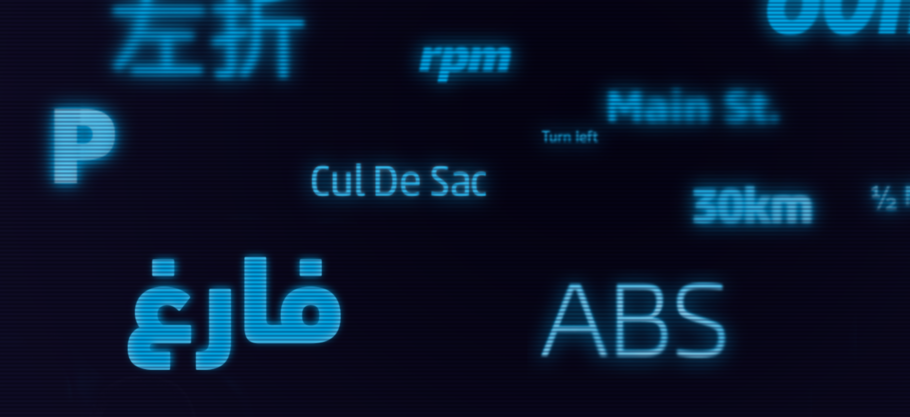
快速获取信息比时速 60 英里重要得多!车用字体必须具有视觉吸引力和品牌一致性,同时还要一目了然,清晰易读。本文展示了一系列可以轻松阅读的字体,这些字体还能够帮助驾驶员在行驶过程中保持注意力。
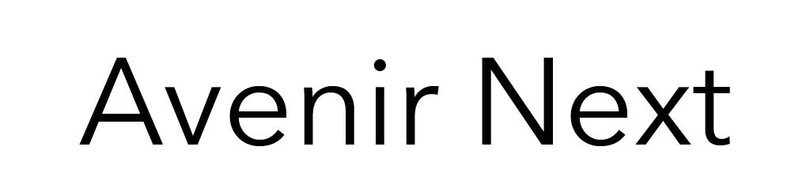
在设计 Avenir® 时,Adrian Frutiger 从过去和未来同时汲取了灵感。Frutiger 在设计中加入了一点有机的人文主义元素,将 Avenir 从早期字体僵硬的几何风格中解放出来。
2004 年,Frutiger 与 Linotype 公司字体设计师小林章一同复刻了 Avenir 字体家族,解决了其屏幕显示的问题。这就是 Avenir Next 字体。几何元素与人文元素的结合造就了 Avenir 字体的高易读性,使其成为汽车人机界面仪表盘和显示器等快速扫视环境下最理想的选择。
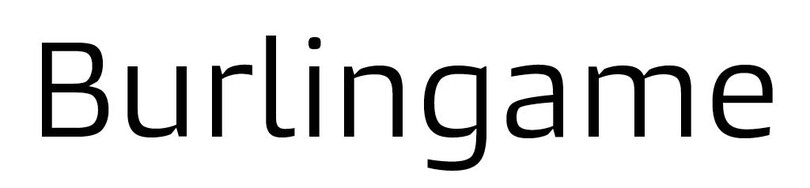
Burlingame® 字体是一款相对较新的字体,它的设计坚实,外形开放、清晰,易读性非常高,尤其对于受限较多的数字化环境。这款字体体现了人文主义及手工质感,根据 Monotype 委托开展的汽车用户界面易读性研究所得到的结果进行了修改,使 Burlingame 成为任何车辆电子仪表盘的不二选择。
Burlingame 字体为了满足汽车显示器的需求融合了多种特性:平整的笔画端头、锐利的转角、“超椭圆” 造型的字碗以及宽松的字间距。其简单的形状和深凹的三角形切口还有助于确保小字号下字体的清晰度和易读性,特别是在低分辨率的屏幕上。
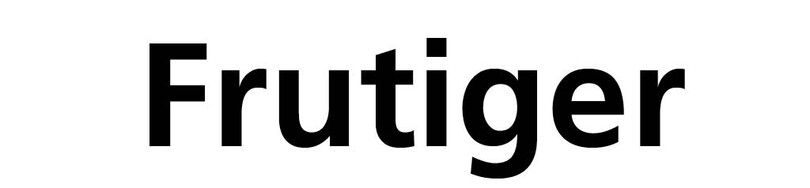
Adrian Frutiger 是世界知名的字体设计师。他的同名字体的设计独具特色,而且用途广泛。Frutiger® 字体最初用于机场导视牌,在远距离及多种角度下阅读都非常清晰。作为一款经典字体,Frutiger 是人文主义无衬线字体的易读性与具有优美几何线条的早期无衬线字体的结合。
Frutiger 因其现代、温暖的外观被许多公司和政府采用。这宽字体的开放性使其非常醒目,其独特的字形避免了与其他字体相互混淆。
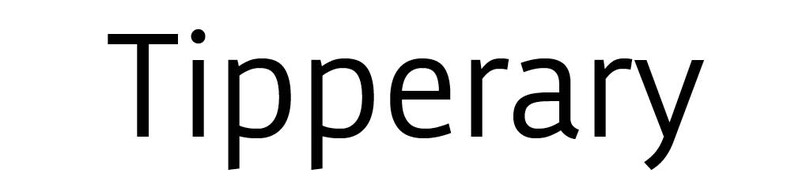
Tipperary™ 是一款等线人文主义无衬线体,具有清晰、开放的字形。其简洁的字符十分易于阅读,也非常适合电子 UI 显示。这款字体的创作中重新诠释并整合了许多经典的字体设计。其结果就是一款在现代显示屏技术受限的范围内仍然表现出色的字体,同时设计上保留了在印刷品中广受欢迎的原有比例和造型。
Tipperary 的字形曲线近似方形,是快速扫视环境下(如汽车仪表,显示器以及界面)的最佳字体之一。
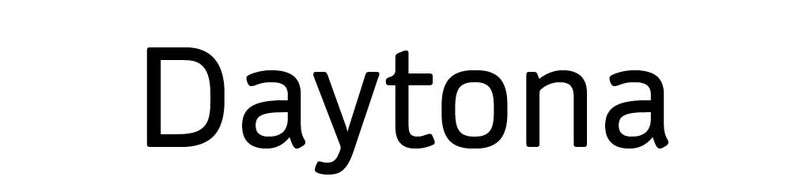
Daytona™ 是由 Monotype 的 Jim Wasco 遵循易读性原则而设计的一款字体。其方正坚实的字符特征遵循人文主义的形状和比例。Daytona 的字形偏窄,可以最大限度地利用空间、提高阅读舒适性。圆润的转角、开放的字怀以及简单的字符形状使 Daytona 成为 Monotype 字体库中最易读的字体之一。
Daytona 字体在几乎所有的屏幕环境中都能表现得非常出色,包括汽车用户界面、数字仪表盘以及 GPS 设备。
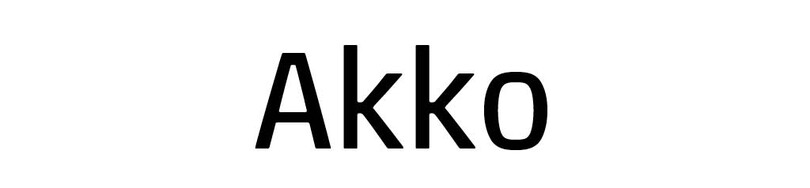
Akko™ 及 Akko Rounded 字体通常会用两个不太可能放到一起的词来描述——“工业感” 和 “精致”。这其实得益于设计师小林章对最初严谨的工业概念的弱化。字体名称来源于其著名设计师的姓名缩写(Akira Kobayashi)。
Akko 设计友好且非常现代化,清晰易读而且又非常时尚。Akko 字形的 “骨感” 的结构降低了其他风格设计中所出现的视觉拥挤现象。
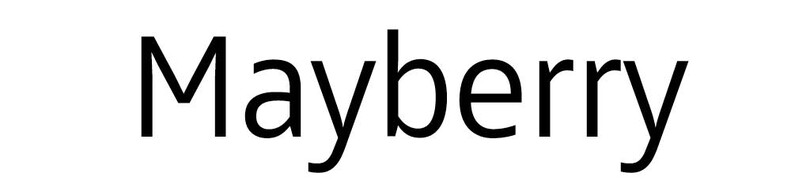
Mayberry 最初是为了模仿 Tiresias™ 字体家族的技术外观而设计的,以便用于机顶盒电视设备及用户界面中。相比 Tiresias,Mayberry 在美学和功能方面都有显著的改进。
Mayberry 包含真正的意大利斜体以及广泛的字重,可以在低分辨率设备上提供高质量的阅读和最好的可读性,同时它还具有一系列能够吸引专业人士的 OpenType 功能。Mayberry 是一款稍窄的人文主义无衬线字体,这样可以在较窄的文本栏中显示更多的可读文本。开放的字怀与垂直的加粗都有助于在低分辨率的情况下保持 Mayberry 设计的可读性。
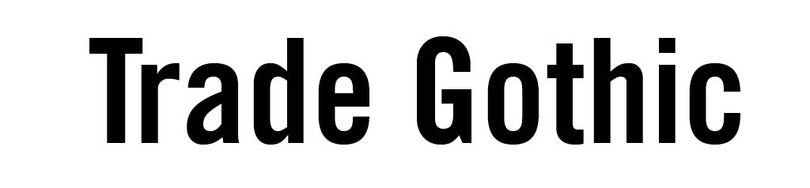
Trade Gothic 字体家族是美国平面设计作品的主打产品,自 1948 年由 Jackson Burke 发布以来一直不断地被使用。这一设计在国际上也很受欢迎,而且曾一度被视为 Helvetica® 家族的竞争对手。
2008 年的版本名为 Trade Gothic Next,这款字体改进并扩展经典系列,还将它引入到一个流行的新时代。这种不和谐却为 Trade Gothic 设计增添了一点质朴的自然主义色彩,这也是许多设计师回归的原因之一。
Trade Gothic Next 是最清晰的早期无衬线字体类型。该字体具有开放的字形及宽松的字间距,让人感觉容易接近,这使其在需要扫视的阅读环境下表现良好。
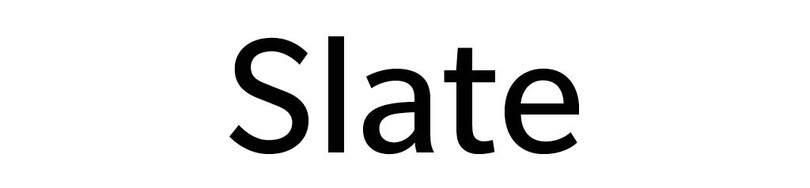
Slate 字体家族将出色的功能及视觉的优雅融合成一种卓越的交流工具。很少有字体具有这种设计的美感和力量。
Slate 的设计者为 Rod McDonald ,一位屡获殊荣的字体设计师和字母绘写师。在四十年的职业生涯中,McDonald 参与了加拿大国家盲人研究所(CNIB)开展的字体易读性和可读性研究项目。 在那里,McDonald 了解到哪些设计特征更适合最大限度地提高字符易读性及文本可读性。
Slate 是一款风格化的人文主义字体,提供了一种温暖的视觉体验。即使在具有挑战性的技术环境中,Slate 也能为用户提供舒适的阅读环境。
Hendrik Weber 的 Unitext 字体设计清晰、简洁,是一款适应性强、识别效率高的无衬线字体,风格介于怪诞无衬线体和人文主义无衬线体之间。
Unitext 深入研究了设计机构对于品牌字体的需求,以及设计师 Hendrik Weber 本人为公司定制字体的经验。由于了解用于品牌推广的无衬线字体的流行度——还有它们的缺点——Weber 开始着手创作一些可以适应不同环境但又不放弃友好性的字体。可读性也是一个重要的考虑因素。
Unitext 是一种新型混合风格的字体,它既具有现代的、前瞻性的外观,又兼备可读性和未来主义的优雅。
完美的易读性。无与伦比的设计。
Monotype 的字体创意总监 Steve Matteson 将这些字体组织到一起来展示一系列可以轻松阅读、并可以帮助驾驶员在行驶过程中保持注意力的字体样本。通过为仪表板或人机交互界面选择合适的字体,您将能够确保您的汽车显示屏清晰易读,并且拥有观众喜爱的无与伦比的设计。